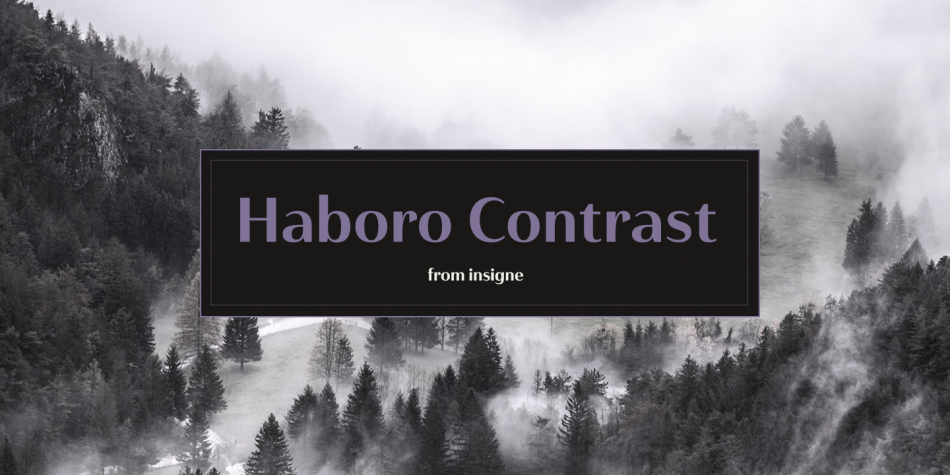
A Haboro Contrast é uma família de fuentes sans serif desenvolvida por Jeremy Dooley. Integre a modernidade do tipo moderno com seu estilo atraente e versátil. Desenvolvido para se destacar, o Haboro Contrast inclui recursos OpenType que vão além da simples estética. Com opções como ligaturas de abertura, conjuntos de estilo personalizados, fracionamento e caracteres em escala menor feitos a mão, este tipo garante que seu trabalho sempre seja atual e envolvente. Se você precisa criar combinações mais complexas para uma declaração apropriada, o Haboro Hyperfamily completo pode ser sua melhor escolha. Combinando os elementos certos, o Haboro Contrast pode capturar a atenção de seus leitores em qualquer contexto.